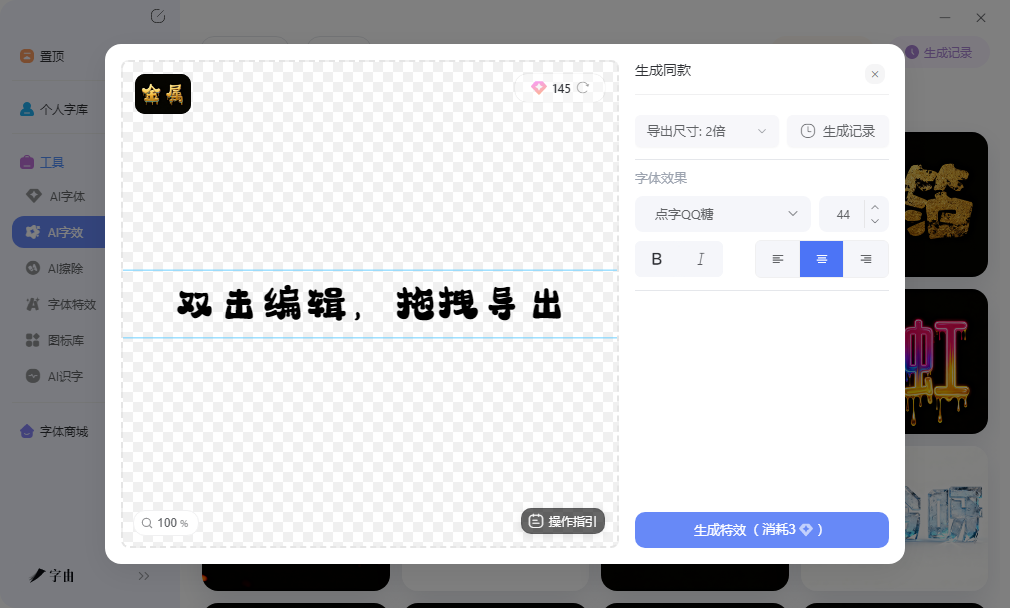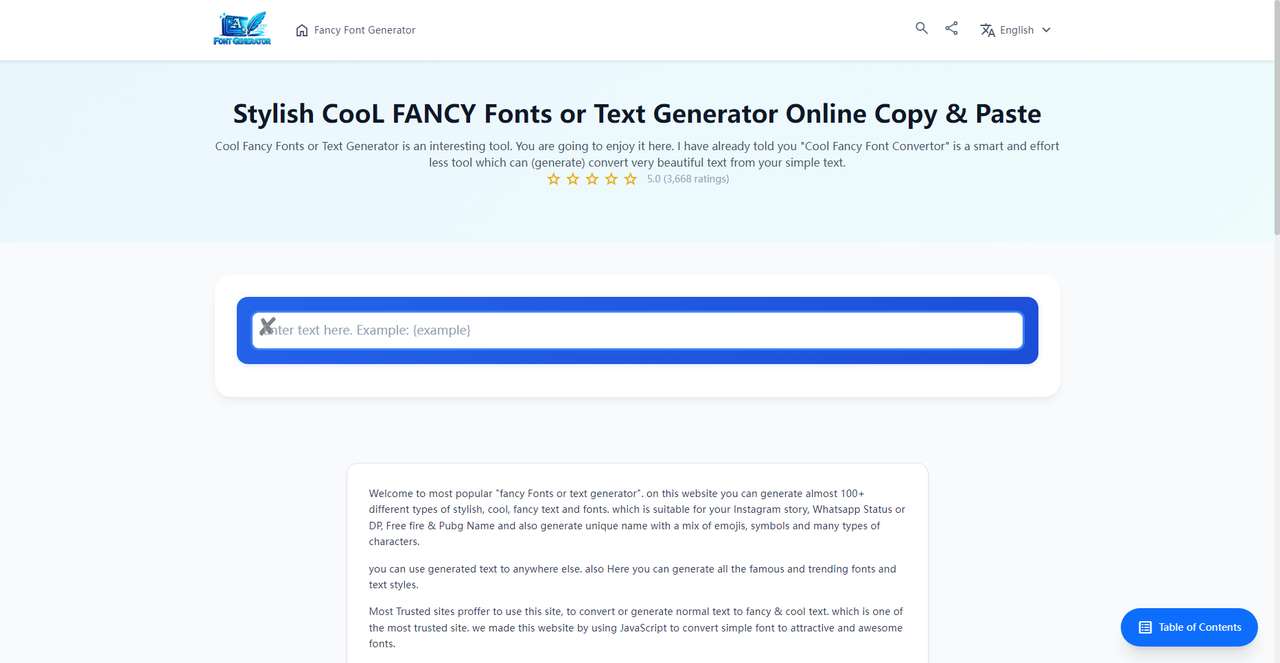
社交媒体文案太单调,试试这几个在线转换工具
如果说你发朋友圈或者写小红书标题,想用特殊字体作为标题,想换点有设计感的,但又不想打开Photoshop调图层样式,更不想为了几个字专门去学设计软件。其实有不少工具可以直接把普通文字转换成装饰字体,复制粘贴就能用,或者生成一张带特效的图片直接插入。这篇文章分享的五个文字转换器在线转换渠道,从中文特效生成到英文Unicode变体都有。
字由的AI字效有网页版,对做社交媒体配图比较实用。打开浏览器就能操作,不需要下载安装客户端,临时在别的电脑上也能生成和下载。输入一段中文文案,比如小红书标题或者朋友圈文案,选择特效模板,可以生成带发光、投影、渐变、金属质感等效果的PNG图片。
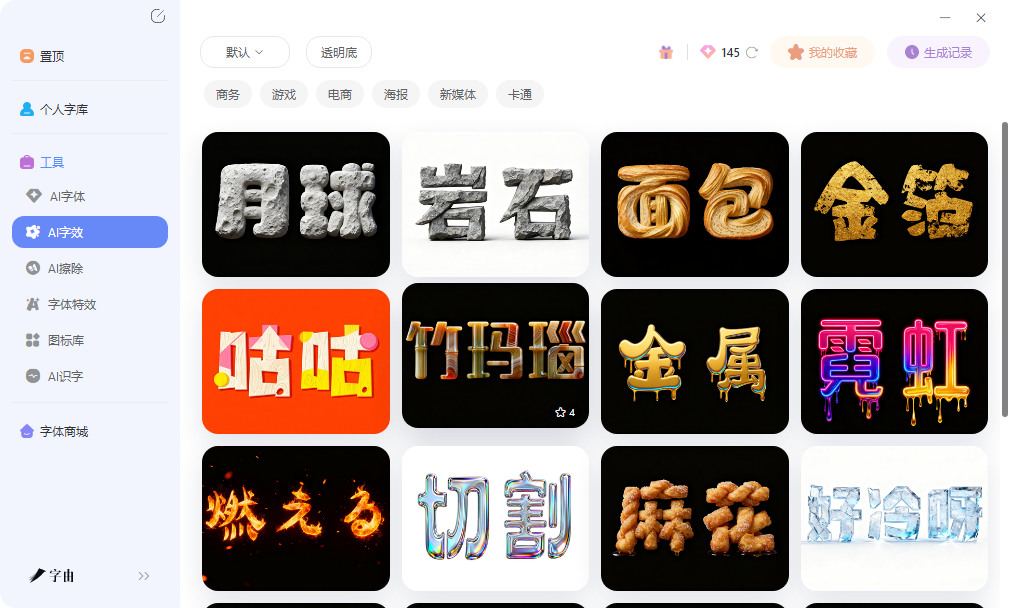
网页版的运行不依赖客户端。不需要先在电脑里装好字由软件,也不需要登录客户端账号,打开浏览器输入网址就能直接使用。这个特性在公共电脑或者临时借用的设备上比较友好,比如在朋友家想快速做一张生日祝福图,或者在网吧临时改一条朋友圈文案,打开网页几分钟内就能出图。
2、CoolFancyFonts
CoolFancyFonts是一个Unicode装饰字符转换工具。输入普通英文文本后,系统会转换为多种花哨变体,包括粗体、斜体、花体、双线体、小型大写字母、泡泡字等。这些变体基于Unicode标准,可以直接复制粘贴到Instagram、Twitter、TikTok、Facebook、WhatsApp等平台的发布框里。
作为文字转换器在线转换的渠道,它的优势在于操作简单、兼容性好。不需要生成图片文件,直接复制特殊字符就能用,后续想修改文字内容直接编辑即可。生成的装饰字符在大多数现代设备和平台上都能正常显示,不会出现乱码。网站上还提供了多种预设风格,点击即可切换,不需要手动调参数。对于需要快速发一条带装饰性文字的社交媒体帖子的人来说,这个工具比较实用。
3、FancyTextGuru
FancyTextGuru提供了多种花哨字体样式转换。输入英文文本后,系统会列出十几种不同的装饰变体,包括Zalgo故障风、中世纪哥特体、草书体、粗体等。用户可以逐行浏览,找到最符合需求的那一款,点击复制即可。
作为文字转换器在线转换的工具,它的优势在于风格跨度大、选择多。和单一样式的转换器不同,这里一次性给出多种变体,省去了逐个试的麻烦。网站上还提供了Lenny Faces表情符号组合、Emoji复制粘贴、文字装饰器等附加功能,可以在生成的文字上进一步添加下划线、删除线、波浪线等效果。对于做新媒体运营、需要频繁更换字体风格来吸引注意力的人来说,这里的批量转换比较高效。
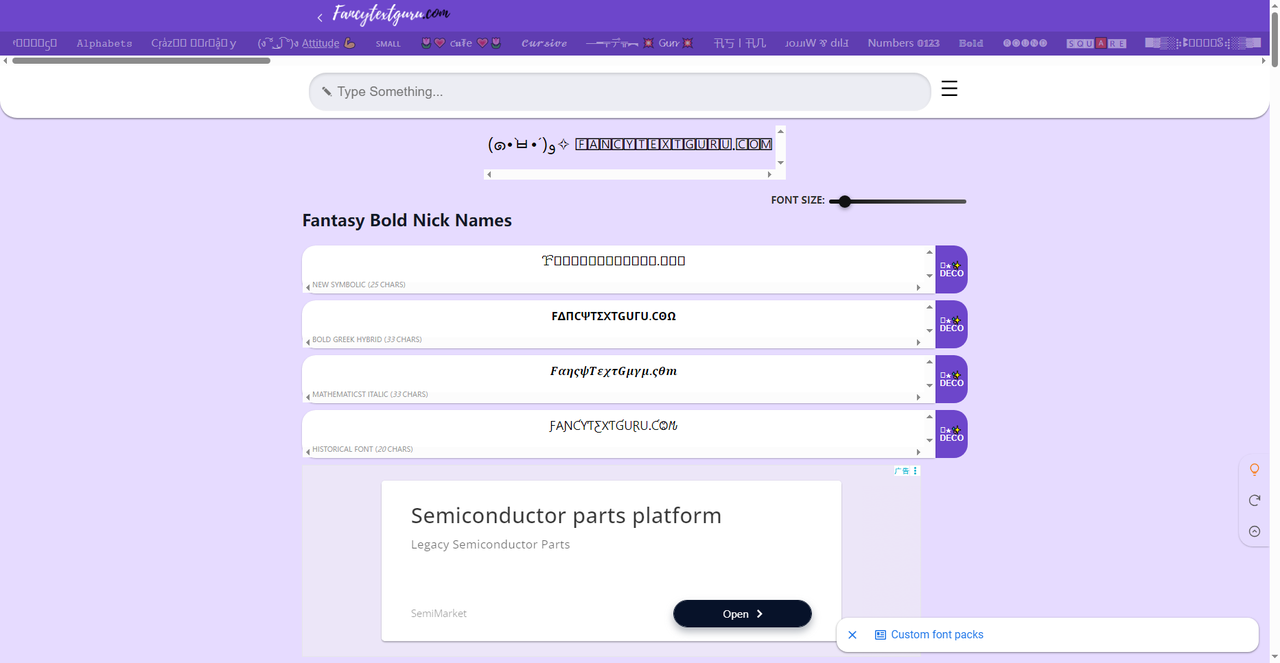
4、FontCopyPaste
FontCopyPaste专注复制粘贴式的字体转换。输入英文文字后,系统会列出所有可用的样式变体,每个变体旁边都有一个复制按钮,点击后可以直接粘贴到目标位置。操作流程极其简洁,输入、浏览、复制三步完成。
作为文字转换器在线转换的渠道,它的优势在于操作极简、响应速度快。网站上没有多余的功能干扰,打开页面就能立刻开始转换。生成的装饰字符基于Unicode标准,在Instagram、Twitter、Facebook等主流社交平台上都能正常显示。对于只需要快速获得一种装饰字体、不想在海量选项里翻找的人来说,这里的直接复制粘贴体验比较顺畅。
5、TextGenerator
TextGenerator 支持多语言文本转换,除了英文外还覆盖了部分其他语言。输入文字后,系统会转换为多种艺术字体样式,包括草书、粗体、装饰体、小型大写字母等。用户可以选择复制为Unicode文本,也可以生成图片格式下载。
作为文字转换器在线转换的工具,它的优势在于输出方式灵活。需要可编辑文字时选Unicode复制粘贴,需要图片素材时选PNG下载。对于做跨语言社交媒体内容的人来说,这里的多语言支持比较实用。网站上还提供了字号调节选项,可以预览不同大小下的显示效果,方便判断在实际发布后的清晰度。
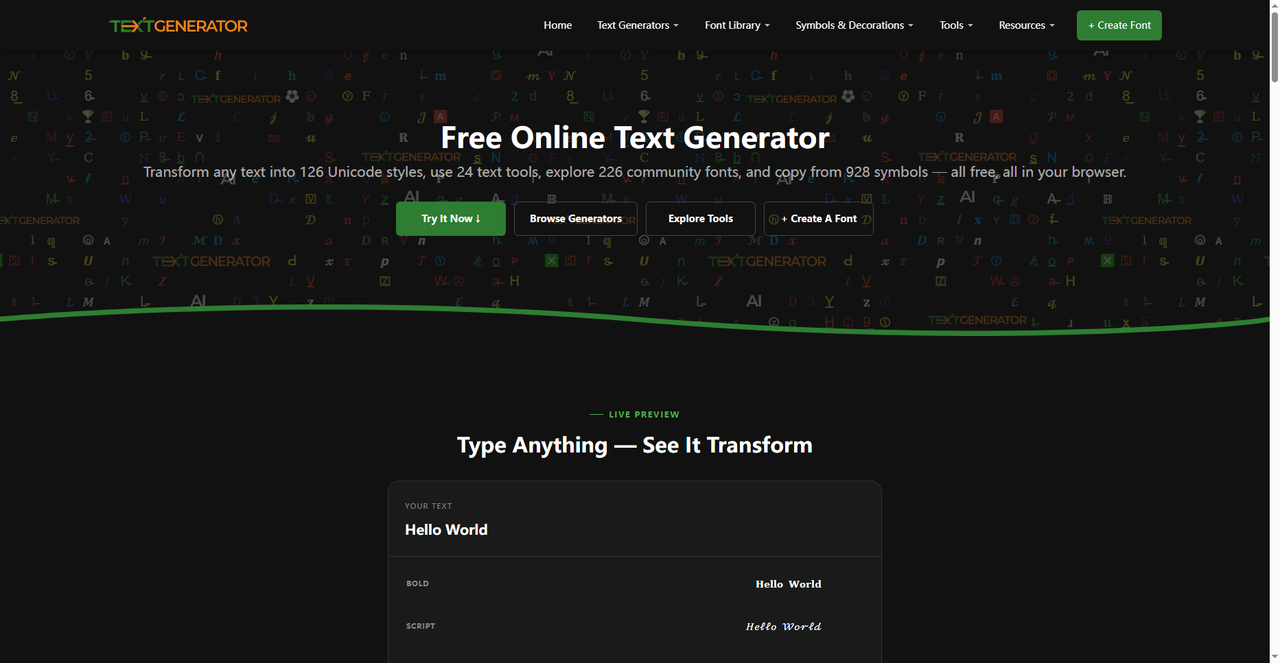
做社交媒体内容,仅仅靠单调的东西是没办法博人眼球的,而字由的AI字效帮你生成透明背景PNG,适合小红书封面、朋友圈海报这类需要视觉冲击力的场景。CoolFancyFonts和FontCopyPaste输出Unicode字符,直接粘贴到Instagram、Twitter发布框就能用。FancyTextGuru风格跨度大,从哥特到泡泡都有覆盖。TextGenerator支持多语言转换,做跨语言内容时比较友好。